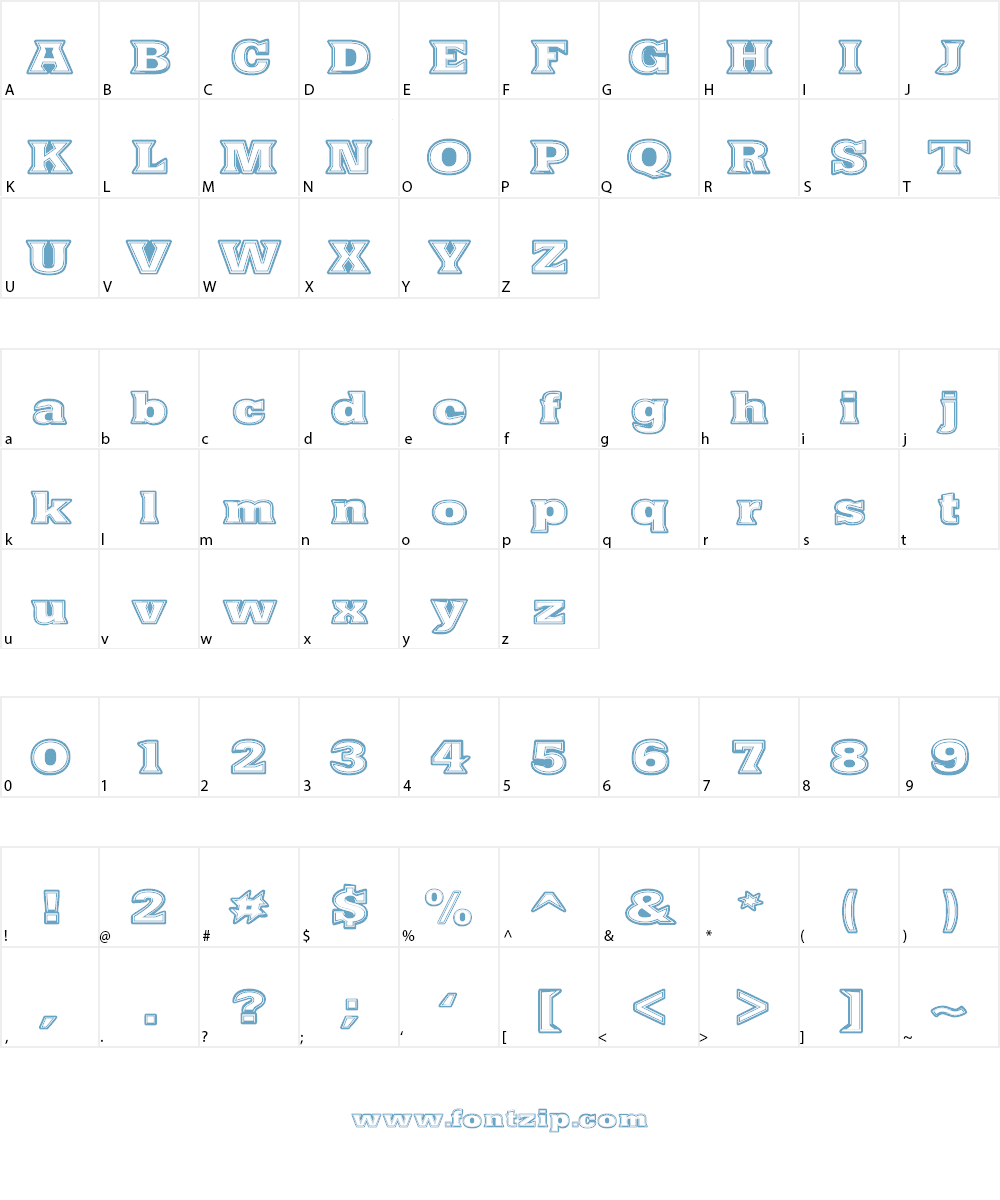
Nacimiento es la hermana outline de mi otra tipografía Yacimiento, es una fuente hueca con outline y fondo en negativo, conserva las características de su hermana pero algo suavizadas. Esta tipografía es perfecta para el diseño de carteles o monogramas, espero la disfruten. Es una tipografía Extra Bold y Semi-Expanded, con tendencia Unicase. La fuente dispone de 372 glifos y sirve para todos los idiomas europeos derivados del latín.